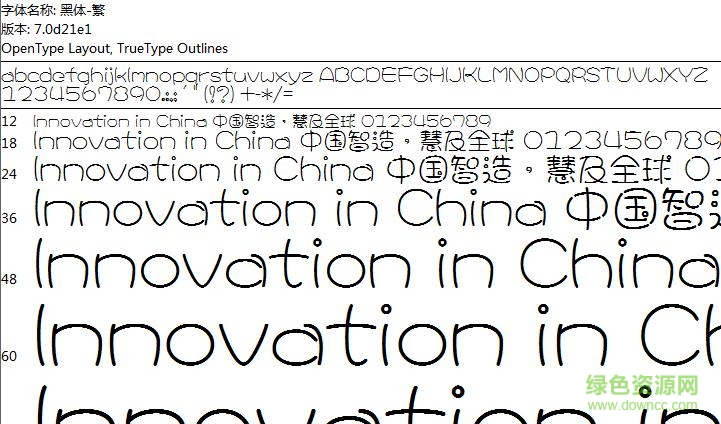
神鳥新生創(chuàng)意體字體ttf是蒼耳字庫中的一款非常具有代表性的藝術(shù)字體,這款字體來自于手寫字體的演化,整體看上去會特別的吸引人,有需要?dú)g迎下載使用!
神鳥新生創(chuàng)意體字體ttf是一款非常有特色的創(chuàng)意字體,這款字體在有些筆畫上進(jìn)行了一定的創(chuàng)意設(shè)計(jì),讓整個字體看上去會顯得圓潤有特點(diǎn),適合用來進(jìn)行廣告的創(chuàng)作!